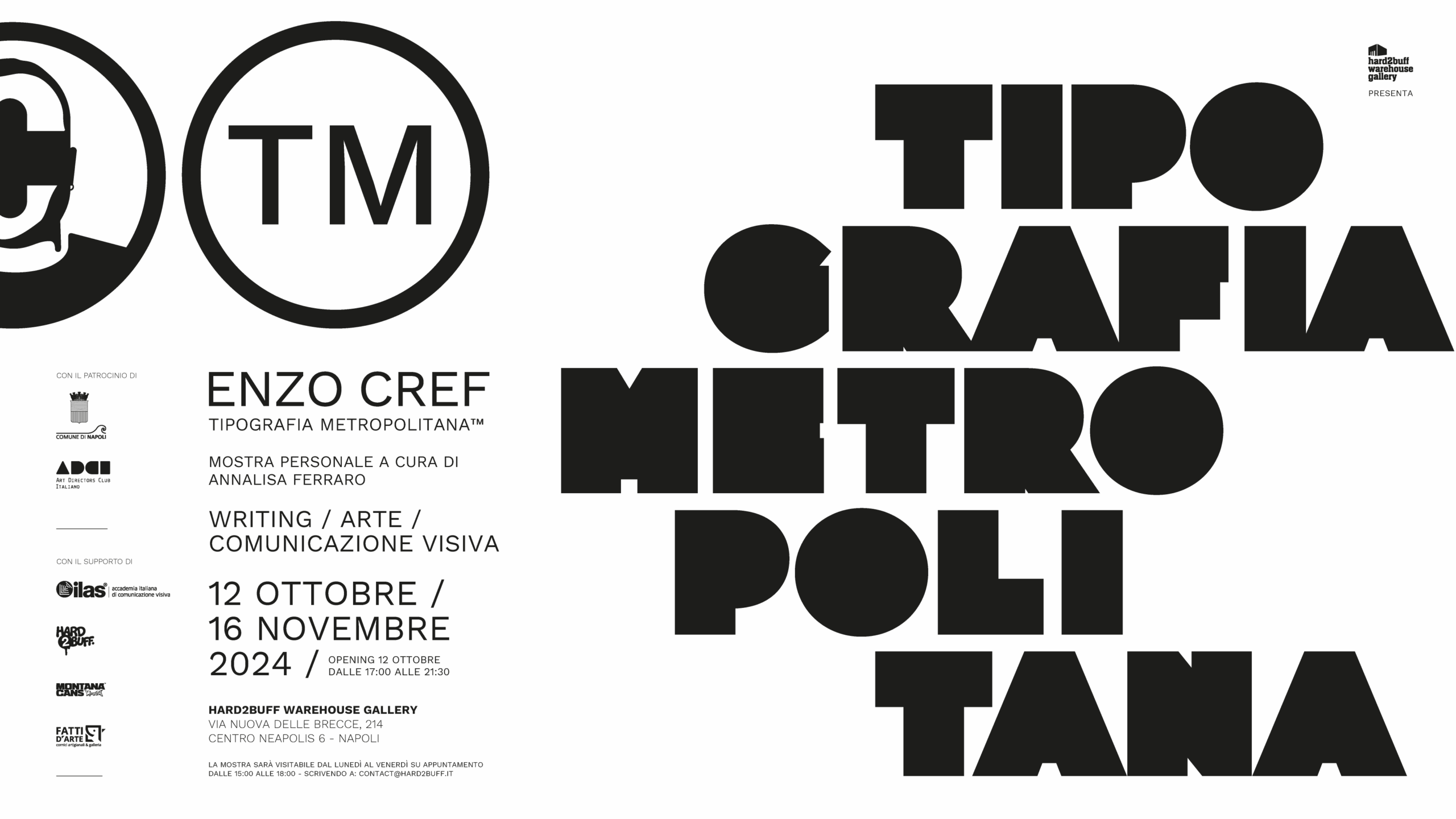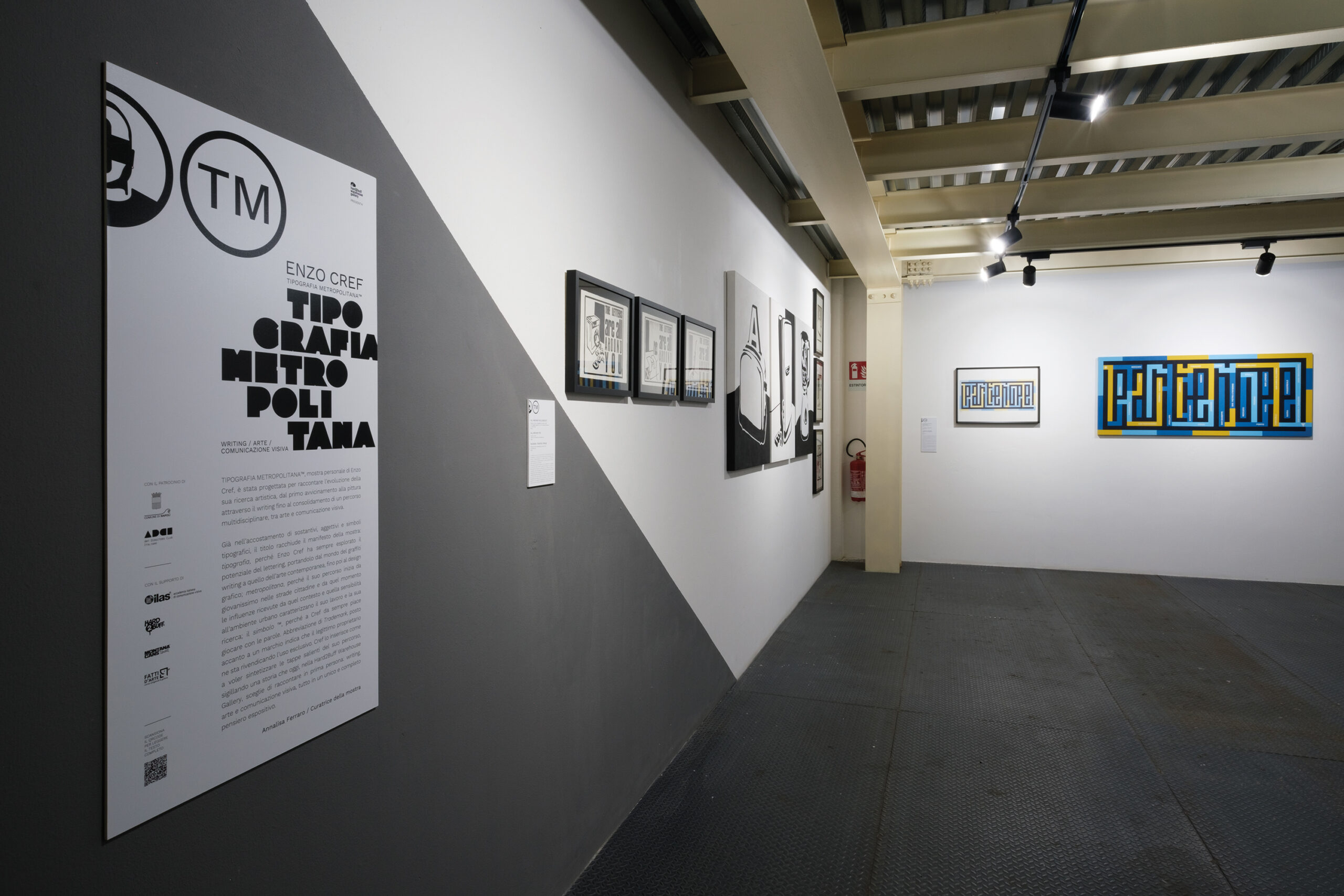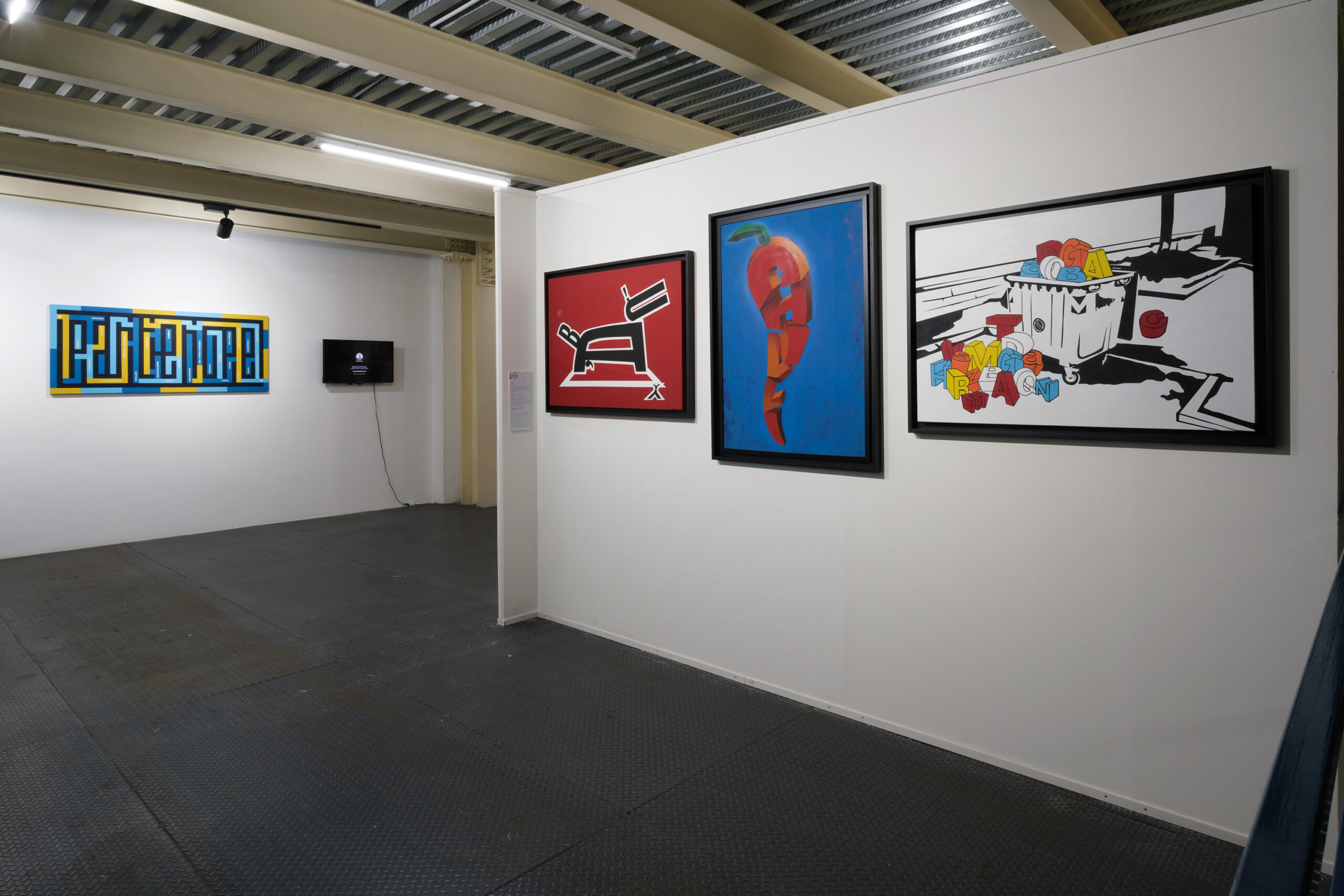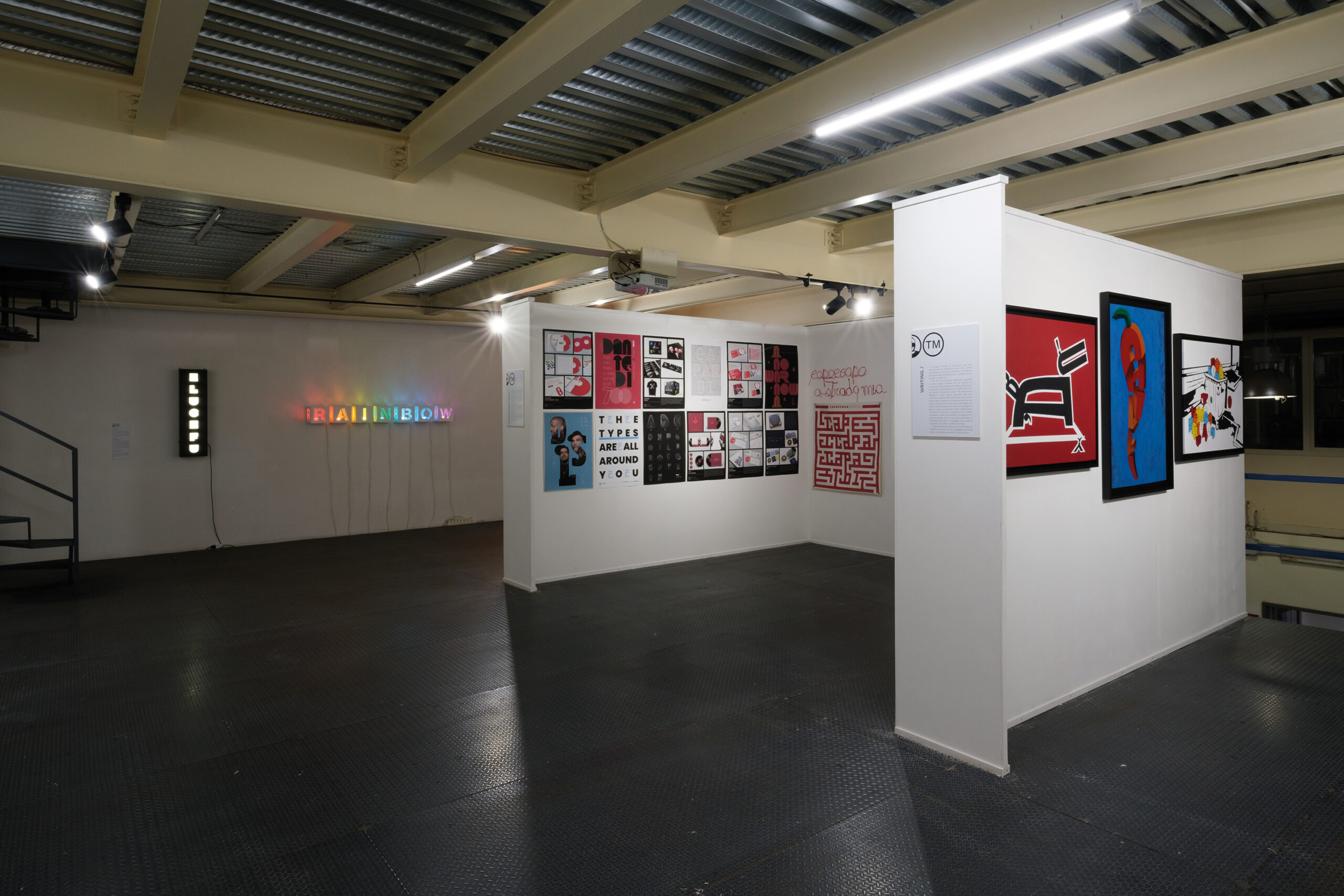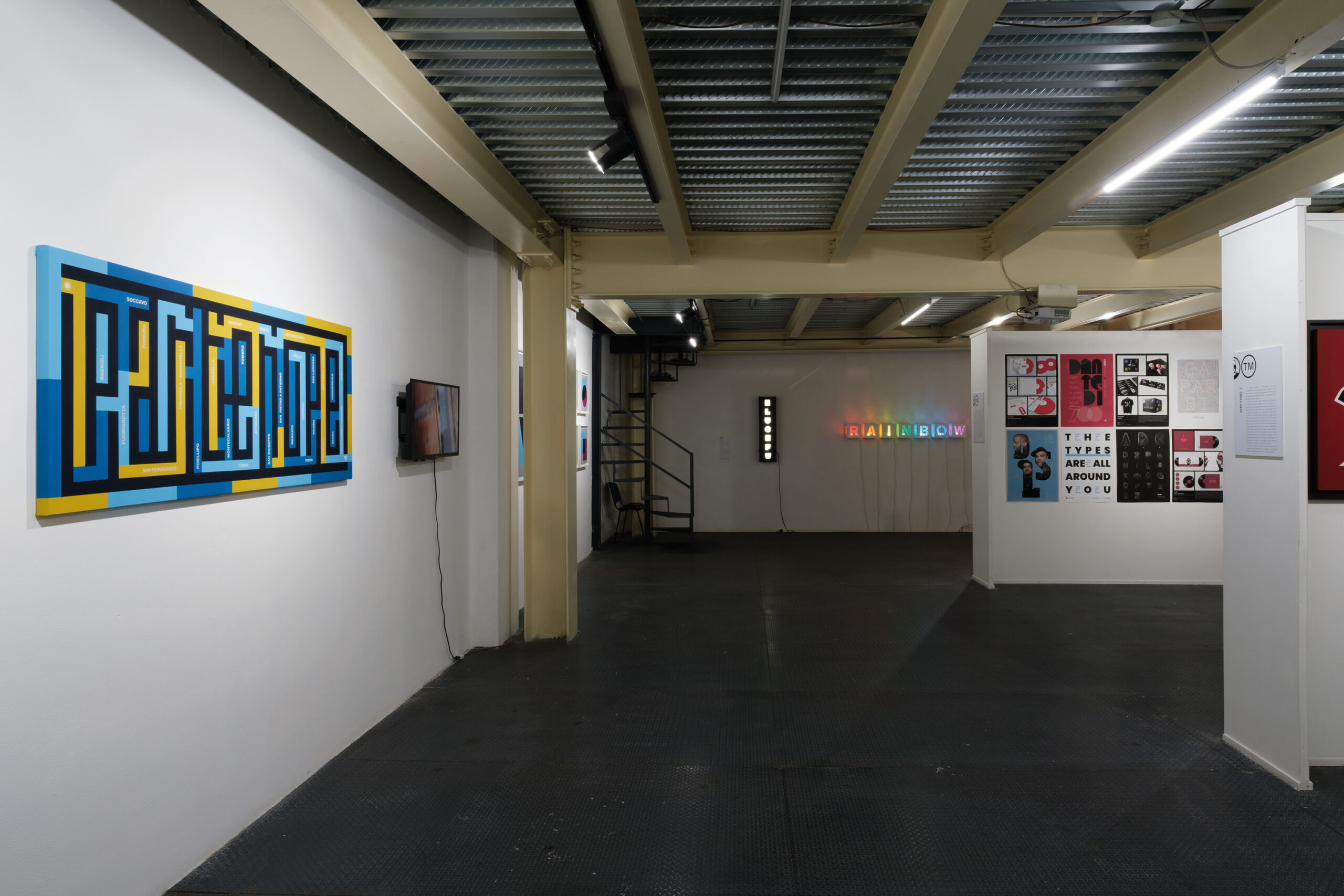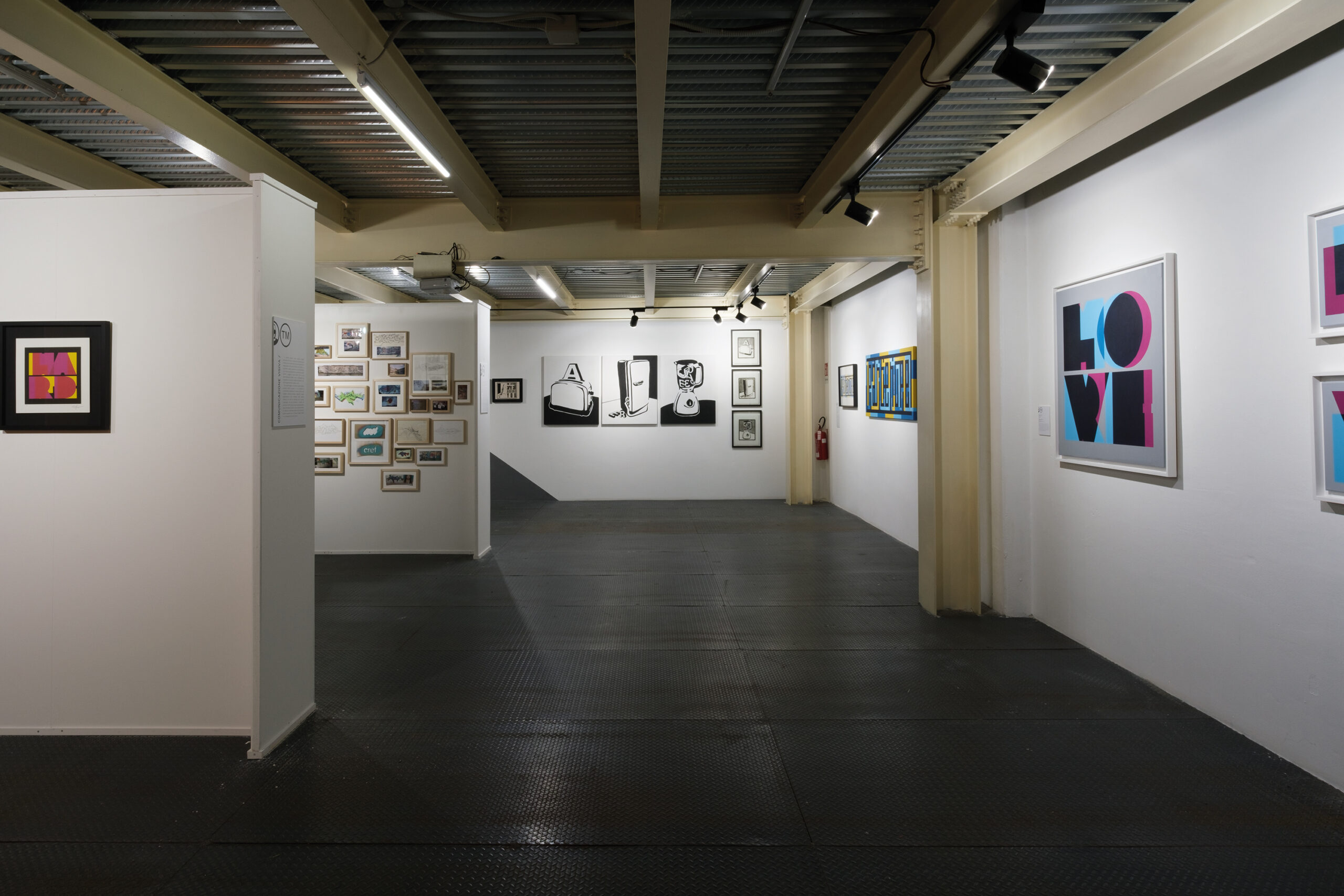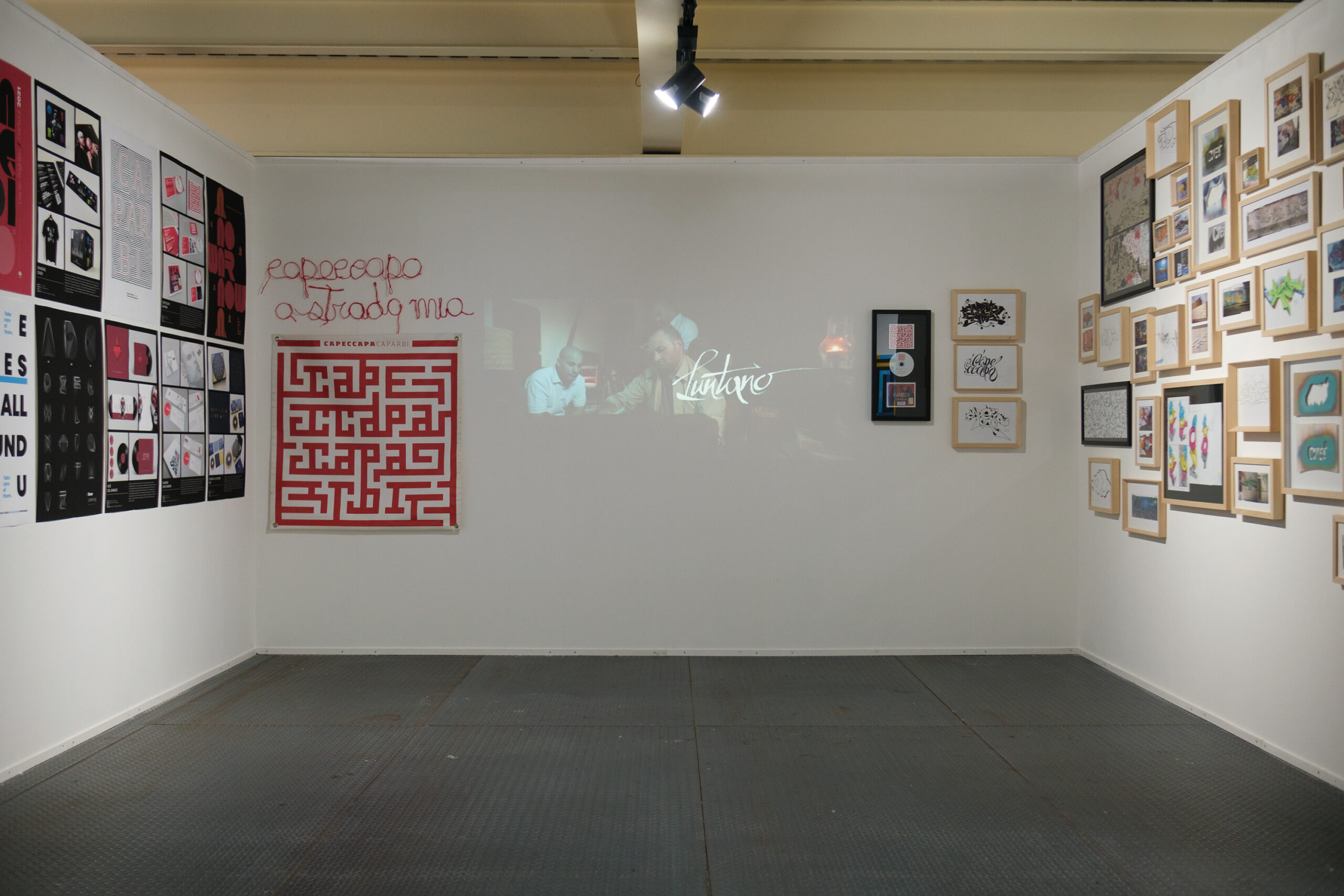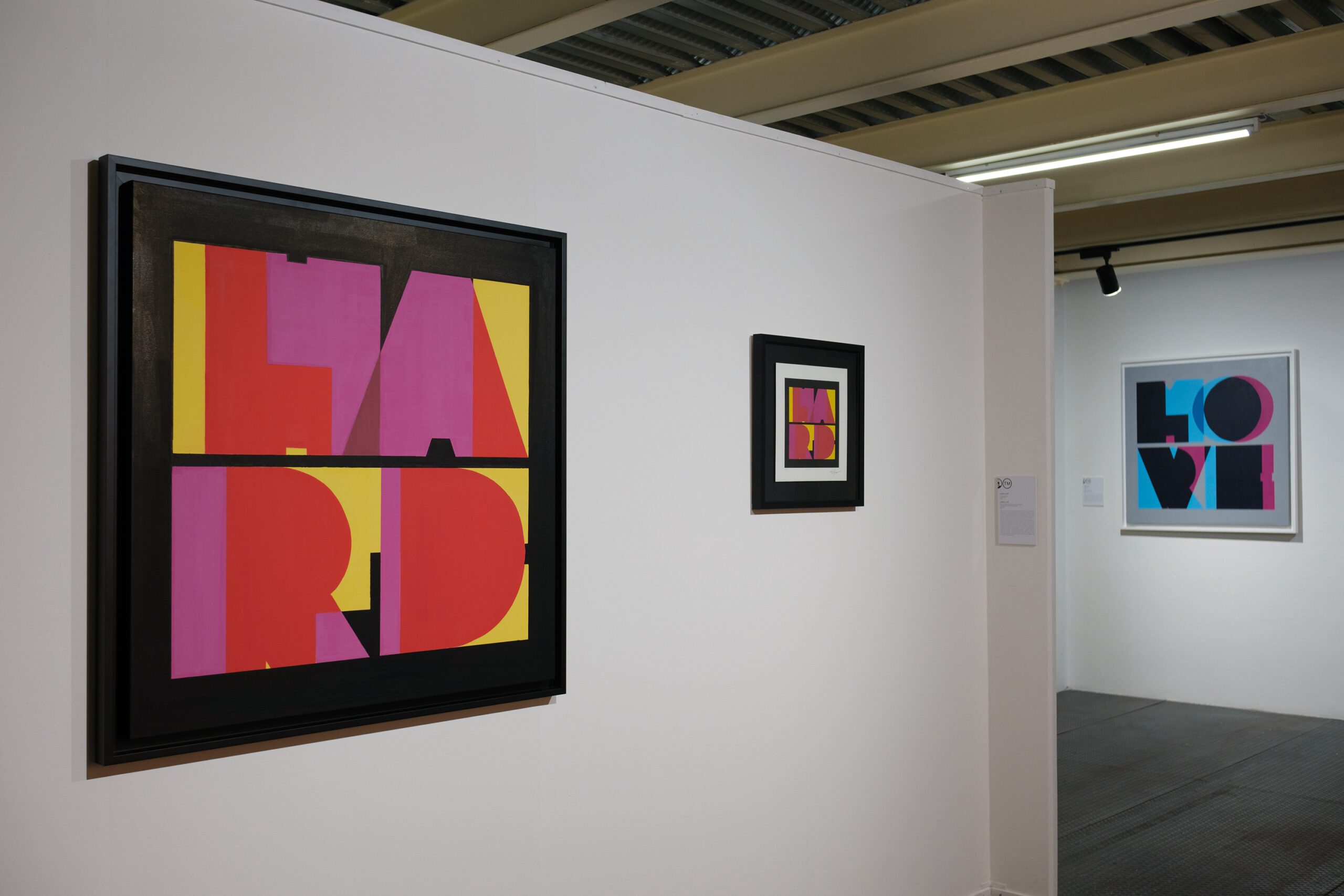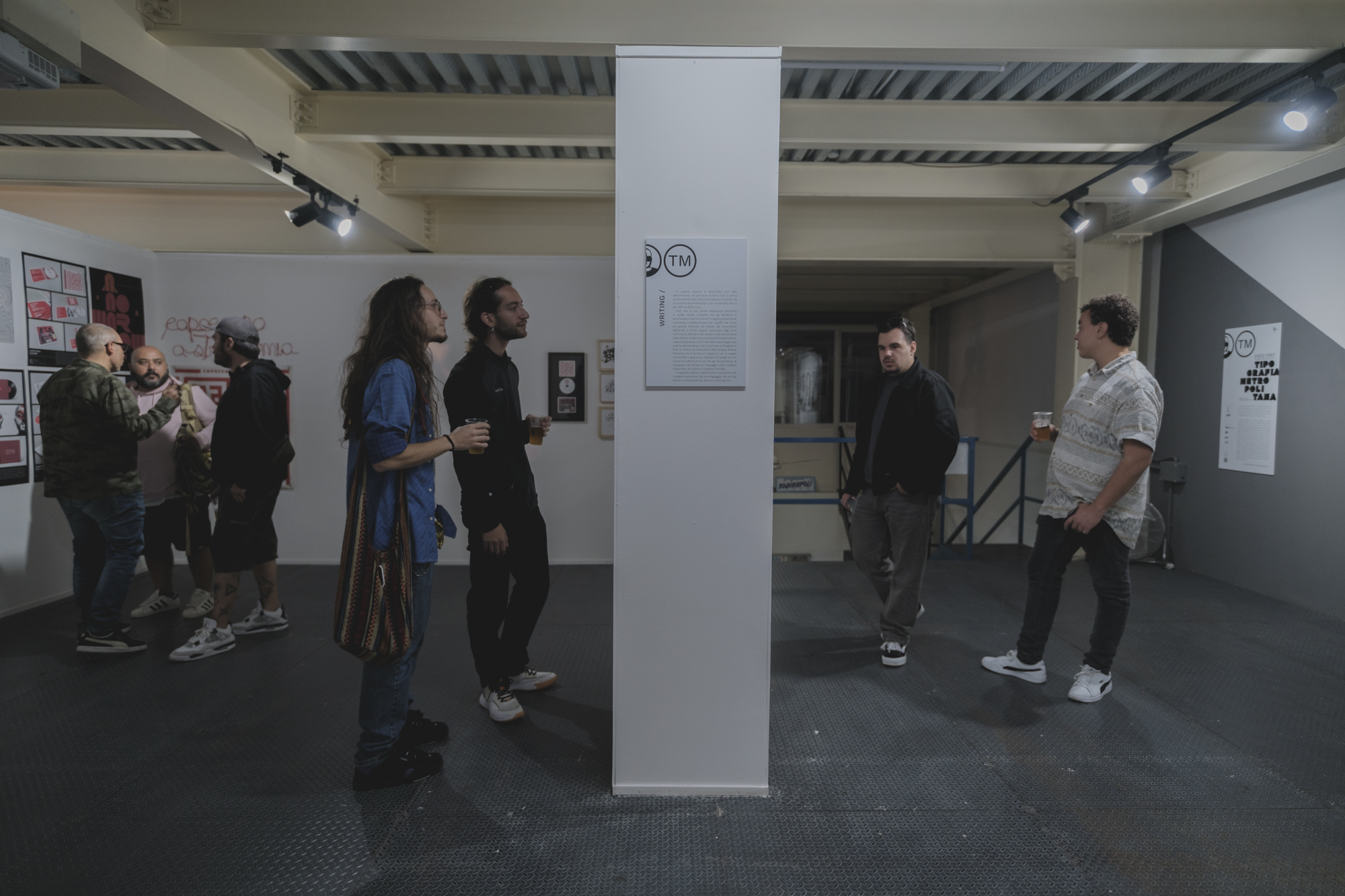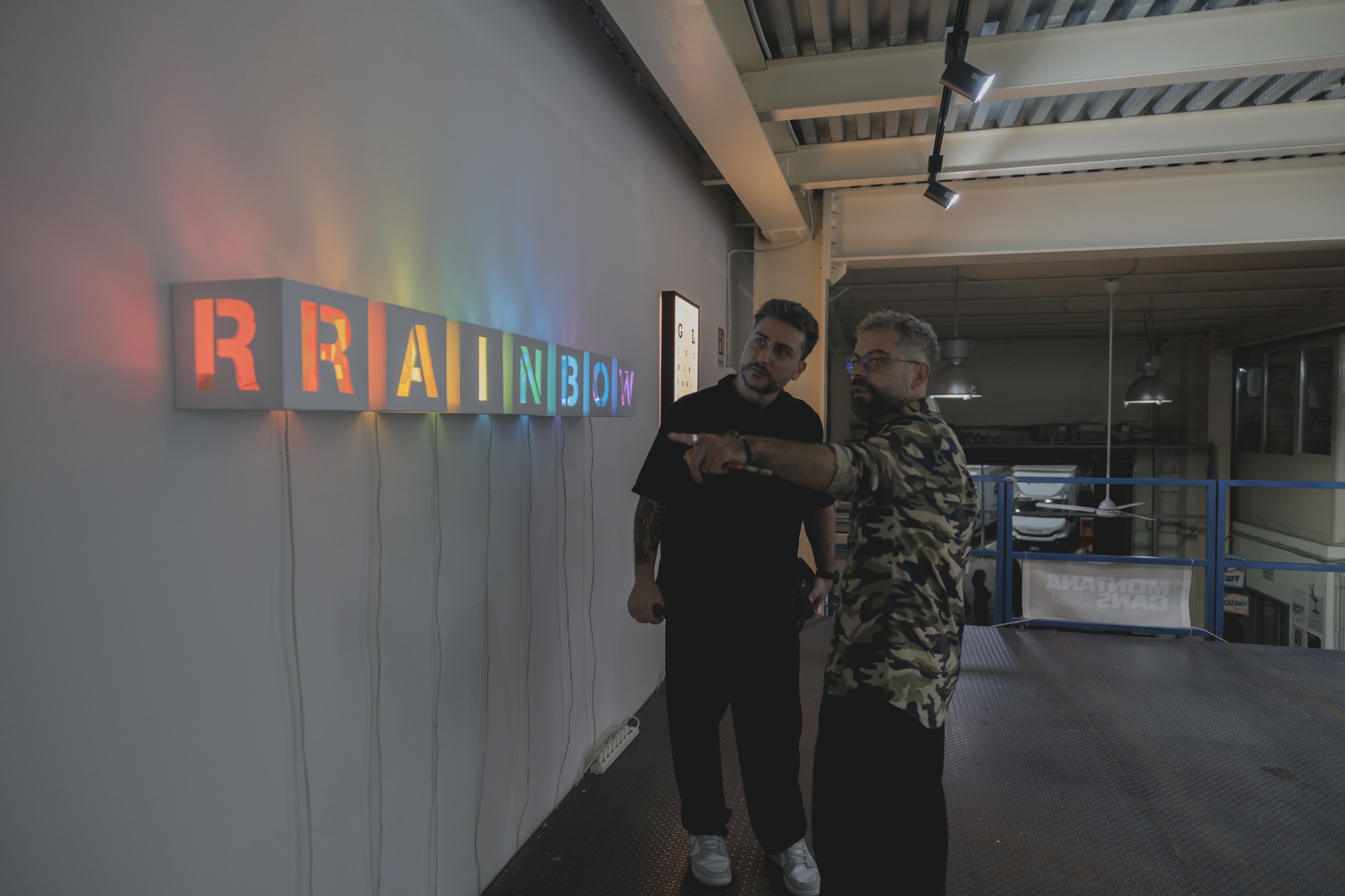
TIPOGRAFIA METROPOLI
TANA™
EXHIBITION
Mostra personale di Enzo Cref
A cura di Annalisa Ferraro
Inaugurata sabato 12 ottobre 2024, presso Hard2Buff Warehouse Gallery, TIPOGRAFIA METROPOLITANA™. WRITING/ARTE/COMUNICAZIONE VISIVA, mostra personale di Enzo Cref, a cura di Annalisa Ferraro, patrocinata dal Comune di Napoli e da ADCI, associazione culturale che dal 1985 riunisce i migliori professionisti della comunicazione.
Già nell’accostamento di sostantivi, aggettivi e simboli tipografici, il titolo racchiude il manifesto della mostra. Da una prima lettura, per chi ha familiarità con il lavoro dell’artista, le connessioni risultano volutamente evidenti: tipografia, perché Enzo Cref ha sempre esplorato il potenziale del lettering, portandolo dal mondo del graffiti writing a quello dell’arte contemporanea, fino poi al design grafico; metropolitana, perché il suo percorso inizia da giovanissimo nelle strade cittadine e da allora le influenze ricevute da quel contesto e quella sensibilità all’ambiente urbano caratterizzano il suo lavoro e la sua ricerca.
Come ogni manifesto che si rispetti, però, il titolo racconta molto più di questo, e anzi gioca con le interpretazioni istintive delle parole per svelarne poi pian piano significati inaspettati e alternativi.
In questo caso, infatti, il termine “Tipografia” non si riferisce alle botteghe artigiane e al lavoro di stampa che viene svolto al loro interno, ma viene utilizzato nella sua originale etimologia: dal greco, týpos, “impronta” e γράφειν, gráphein, “scrivere”, con il quale si indica la scrittura di un testo attraverso l’utilizzo di matrici incise o di caratteri tipografici, e l’impronta che essi lasciano.
Il titolo così composto, “Tipografia Metropolitana”, allude quindi a quel tipo di comunicazione visiva che pervade le città moderne: pubblicità, street art, graffiti, insegne luminose, manifesti, schermi che mostrano senza sosta slogan commerciali, immagini e messaggi che si mescolano in un flusso continuo, definendo il paesaggio urbano contemporaneo.
L’ispirazione di Enzo Cref nasce dall’impronta che questa combinazione di elementi visivi ha lasciato in lui fin da bambino. La mostra esplora le evoluzioni del segno urbano nella sua produzione artistica, partendo da queste prime influenze, inconsapevoli e spontanee, fino alla costruzione consapevole di un linguaggio complesso e stratificato, che ha dato vita a uno stile solido e riconoscibile.
Sin dalle prime rielaborazioni di ciò che aveva osservato e immagazzinato, Cref ha cercato di trasformare il caos visivo delle città moderne in una narrazione ordinata e lineare.
Il lettering è diventato il suo strumento di lavoro: lettere, parole e frasi, inizialmente studiate nel loro aspetto strutturale e nel rapporto con l’ambiente circostante, indagate poi nella loro capacità di raccontare storie e veicolare emozioni, di parlare di società, identità e cultura urbana.
Dopo un percorso lungo più di vent’anni, l’artista avverte la necessità di mettere un “punto e a capo” alla sua produzione, fermarsi, respirare e iniziare un nuovo ciclo. Ancora una volta lo fa giocando con le lettere e con i significati che possono acquisire. È per questo che il simbolo TM viene apposto a chiusura del titolo. Nel linguaggio tipografico universale abbrevia Trademark: posto accanto a un marchio non registrato o in via di registrazione, indica che il legittimo proprietario ne sta rivendicando l’uso esclusivo, diffidando da eventuali usi impropri. In questo caso, Cref lo inserisce come a sintetizzare le tappe salienti del suo percorso e per sigillare una storia che oggi, in questo spazio, sceglie di raccontare in prima persona: writing, arte e comunicazione visiva, tutto in un unico e completo pensiero espositivo.